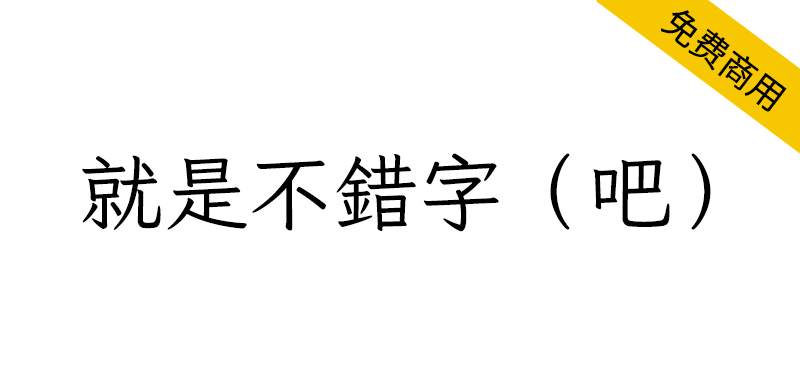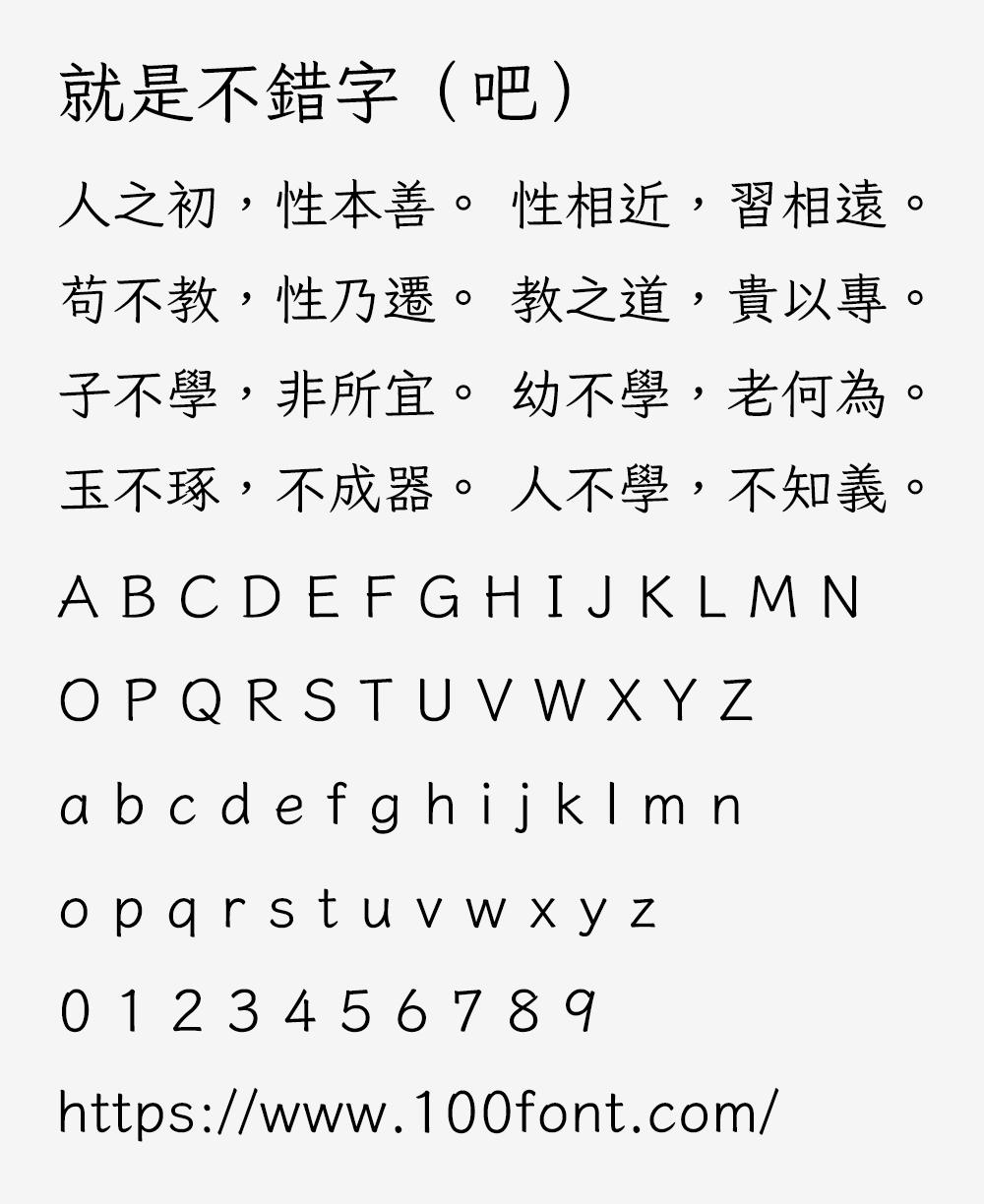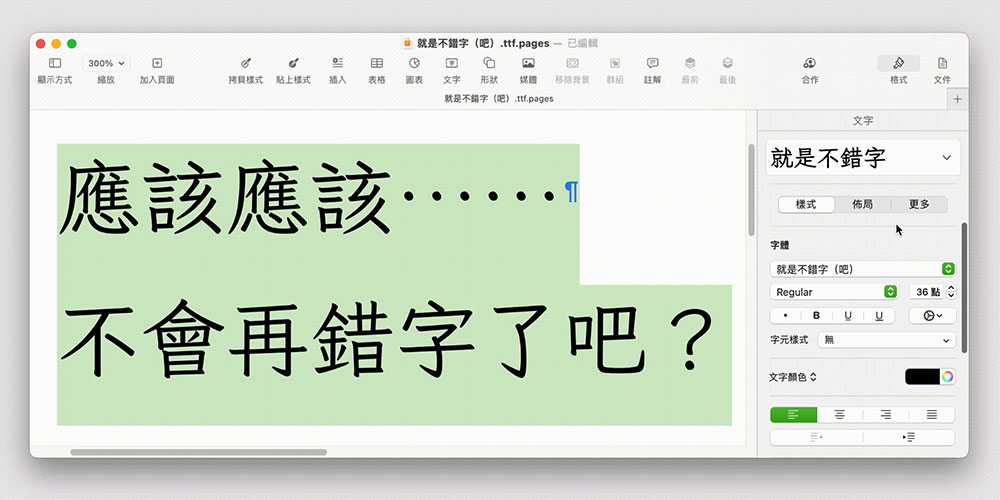
就是不错字(吧)是基于 芫荽 字型改作,由justfont的团队制作,以OpenType 实现输入常见错字即会自动改正功能的开源繁体中文字型,旨在协助所有被生活中各式错字所困扰的朋友。
只要在支援OpenType 的设计或文书软体中,用就是不错字(吧)输入常见错别字词,将会主动替换为正确用字。如:「在次」替换为「再次」、「因該」替换为「應該」、「以經」替换为「已經」、「收尋」替换为「搜尋」等。
就是不错字(吧)错字词库由justfont 团队工人智慧收录,所支援修正之常见错字包含华语、台语、客语常见误用字词,用法标准以教育部辞典与推荐用字为主。
本词库由justfont 团队工人智慧编撰,约能达成87% 正确率,无法保证在所有词汇应用下皆正确,还请见谅。
另因不同的文字组合语意千变万化,就是不错字(吧)字型为避免误杀,部分字词已人工排除。以「以經」为例,若您输入「以經理的意見為主」,将不会自动替换为「已經」。另如「他剛剛從新竹過來」,也不会将「從新」替换为「重新」。